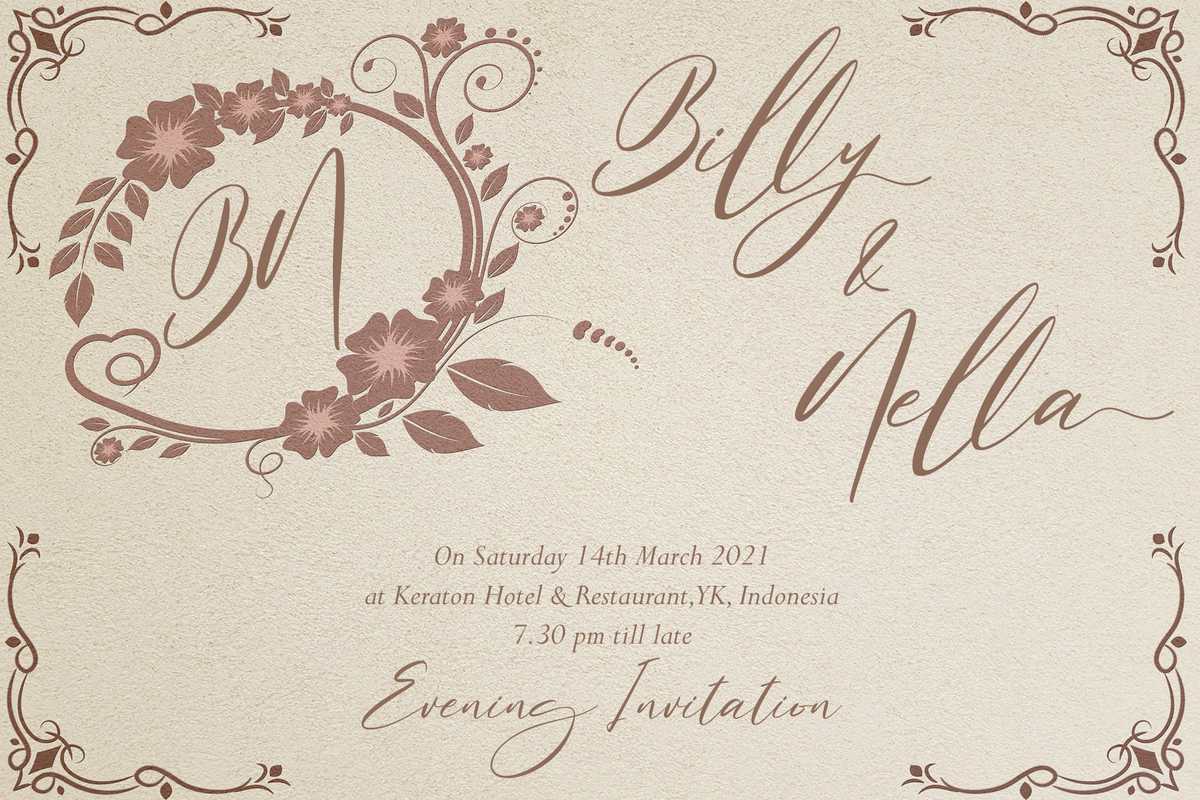
Belastine是一款风格独特、精致的字体和书写字体。它的设计风格优美多样,需要个性化的风格,如婚礼庆典、感谢卡、婚礼、问候卡、标志等等。此字体编码,意味着您可以访问铭文和Swashease!Belastine是一款风格独特、精致的字体和书写字体。它的设计风格优美多样,需要个性化的风格,如婚礼庆典、感谢卡、婚礼、问候卡、标志等等。此字体编码,意味着您可以访问铭文和Swashease!